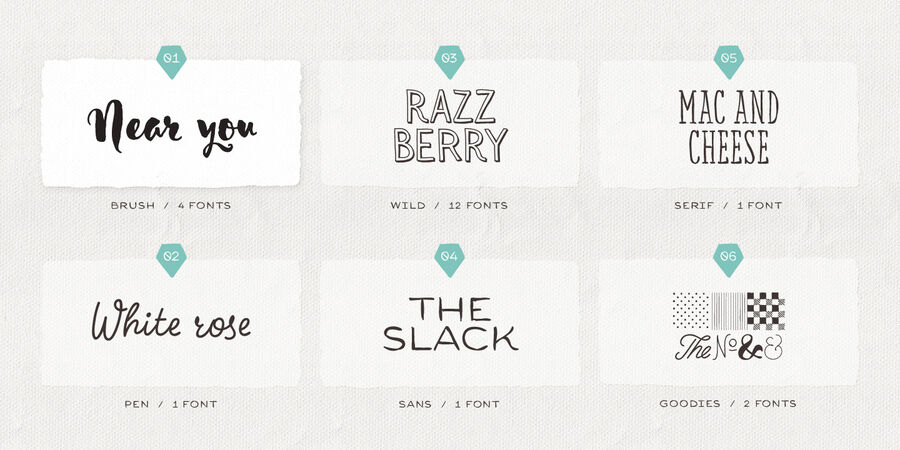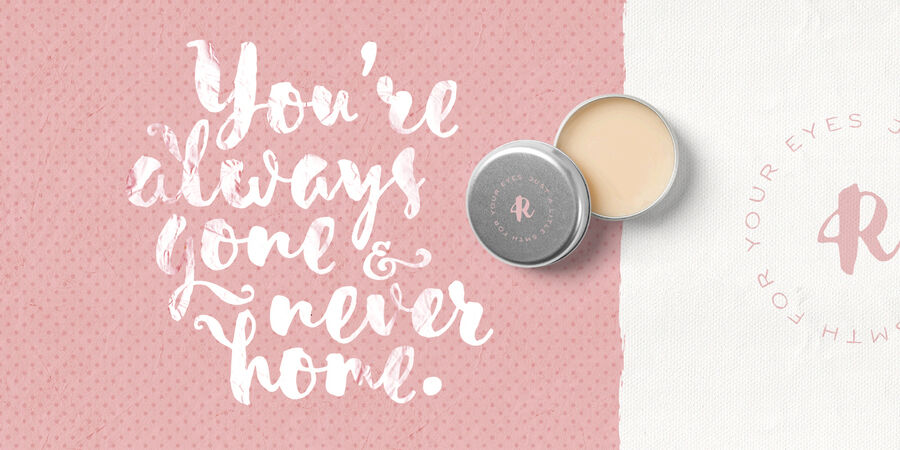
Шрифт Sensa – це сімейство шрифтів ручної роботи, що складається з 21 накреслення. Серед інших рукописних шрифтів цей поділяється на 6 підродин, кожна з яких вносить свій внесок у широкий діапазон настроїв – Sensa Brush, Sensa Pen, Sensa Wild, Sensa Sans, Sensa Serif та Sensa Goodies. Виберіть будь-який із шрифтів Sensa в якості провідного, а решта шрифтів можуть з легкістю супроводжувати його. Щоб працювати разом у всіх можливих комбінаціях, всі шрифти в цьому наборі створені з урахуванням цієї простої ідеї. Шрифт Sensa можна застосувати практично для будь-якого дизайнерського проекту – від реклами, упаковки, редакторських і брендингових робіт до веб, соцмереж та екранних проектів. Для краси та ніжних відчуттів або для більш чоловічого та сильного спілкування – у вас є широкий вибір. Гарнітура підтримує кирилицю. 2 шрифти Sensa доступні БЕЗКОШТОВНО. Функції OpenType: стилістичні альтернативи, контекстуальні альтернативи, розчерки, локалізовані форми. Шрифт розроблений командою Fontfabric в 2015-2018 роках.
Асоціації з сімейством шрифтів Sensa BrushОсобистість і характер гарнітури:
динамічний, свіжий, неохайний, веселий, солодкий, легковажний, сучасний, емоційний, рідкий, лихий, рухливий, непосидючий, ягідний, фруктовий, мультяшний, яскравий, смачний, смішний, добрий, наївний, милий, М'який, ремісничий, рукотворний, ручний, домашній, затишний, сімейний, екологічний, доброзичливий, довірчий, зелений, натуральний, природний, теплий, ламповий, апетитний, здоровий, грайливий, потішний, прикольний, живий, оригінальний, привітний, характерний, святковий, соковитий, стиглий, крафтовий, радісний, пустотливий, весняний, літній, кустарний, саморобний, приємний, няшний, щасливий, симпатичний, артізанальний, недбалий, моторний, вільний, сільський, модний, помітний, виразний, артистичний, органічний, дитячий, жартівливий, пещений, колоритний, творчий, усміхнений, дівчачий, лісовий, дивний, осінній, вернакулярний, подростковый, казковий, химерний, цікавий, складний, епатажний, дикий, страшний, макабричний, декоративний, кущистий, рослинний, кріповий, самобутній, божевільний, карикатурний, нервовий, запальний, прозорий, легкий, тонкий, холодний, повітряний, невагомий